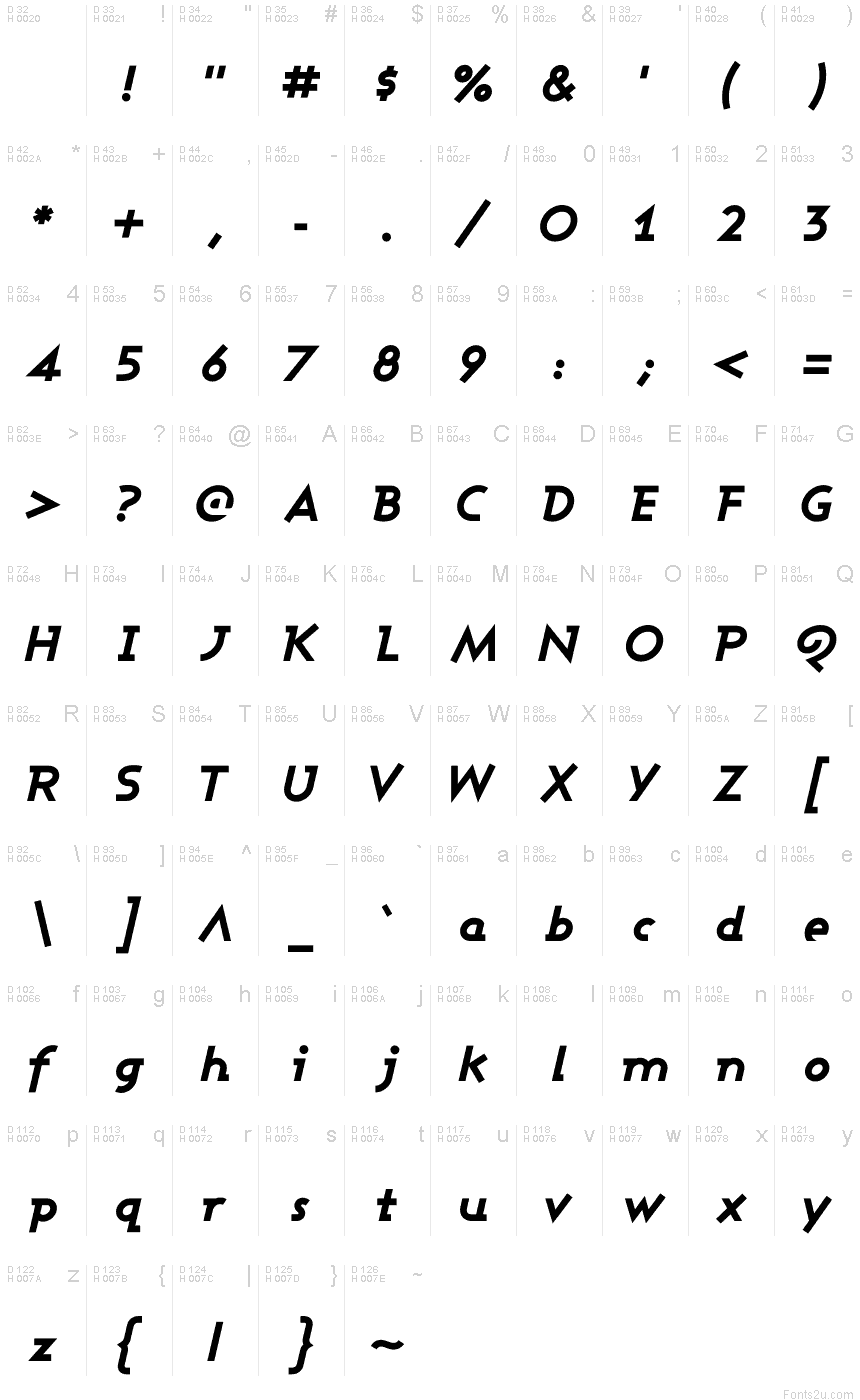
Ashby Extra Bold Italic
Ashby Extra Bold Italic autorstwa Robby'ego Woodarda to darmowy, retro krój pisma typu display o wyrazistym, dynamicznym charakterze. Grube, „atramentowe” linie wyglądają niemal jak ręcznie wycinane, z ostrymi przekątnymi krawędziami, które wcinają się w światło, oraz zaokrąglonymi łukami, które nadają całości zabawny, a nie surowy wydźwięk. Silne pochylenie kursywy nadaje każdemu słowu dynamiki, jakby było w ciągłym ruchu – to świetny wybór, gdy chcesz, aby Twój komunikat był głośny, pewny siebie i nieco buntowniczy.
Ashby Extra Bold Italic sprawia, że nagłówki natychmiast przyciągają wzrok, dzięki czemu ten darmowy font jest naturalnym wyborem do odważnych logotypów, plakatów, okładek albumów, opakowań, ulotek wydarzeń czy grafik do mediów społecznościowych. Jego zwarty rytm i solidna waga sprawdzają się nawet w dużych rozmiarach na ekranie i w druku. Aby stworzyć proste zestawienie, pozwól Ashby przejąć „krzykliwe” elementy, a całość zrównoważ czystym, neutralnym bezszeryfowym krojem pisma w tekście głównym, aby zapewnić czytelność i uderzający efekt.